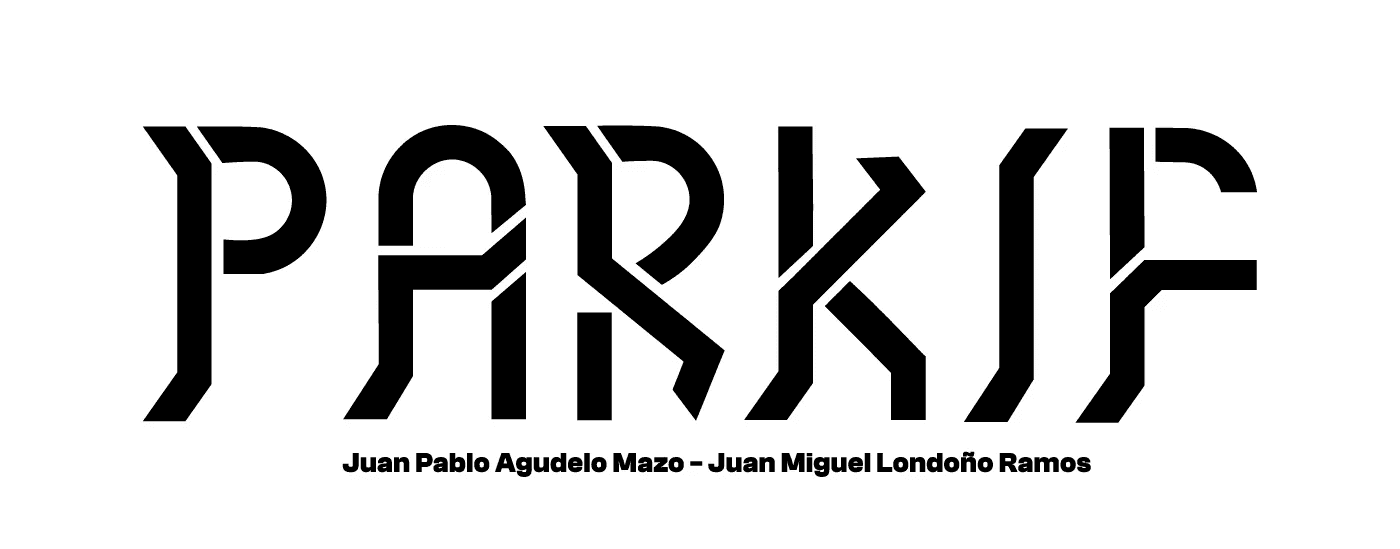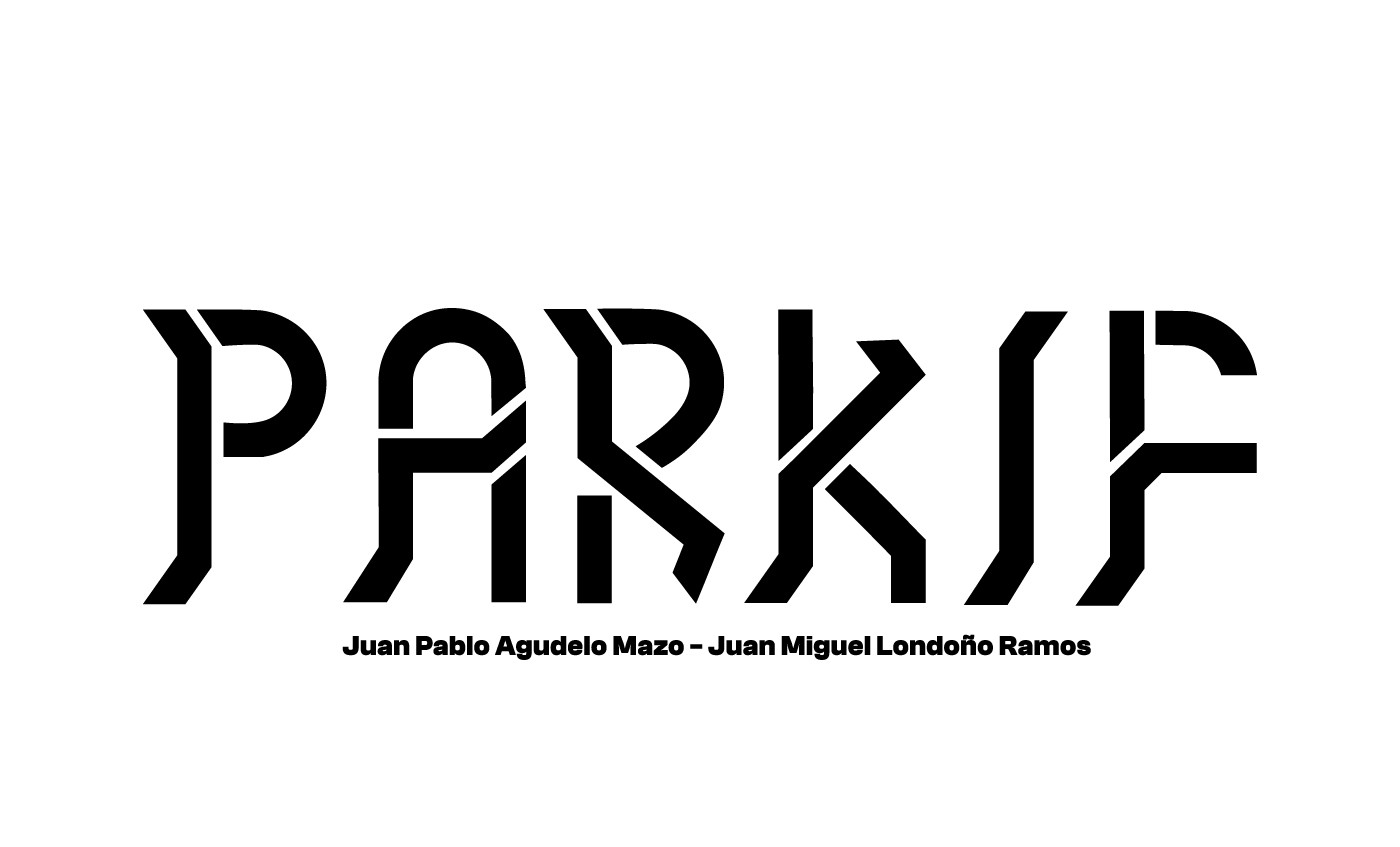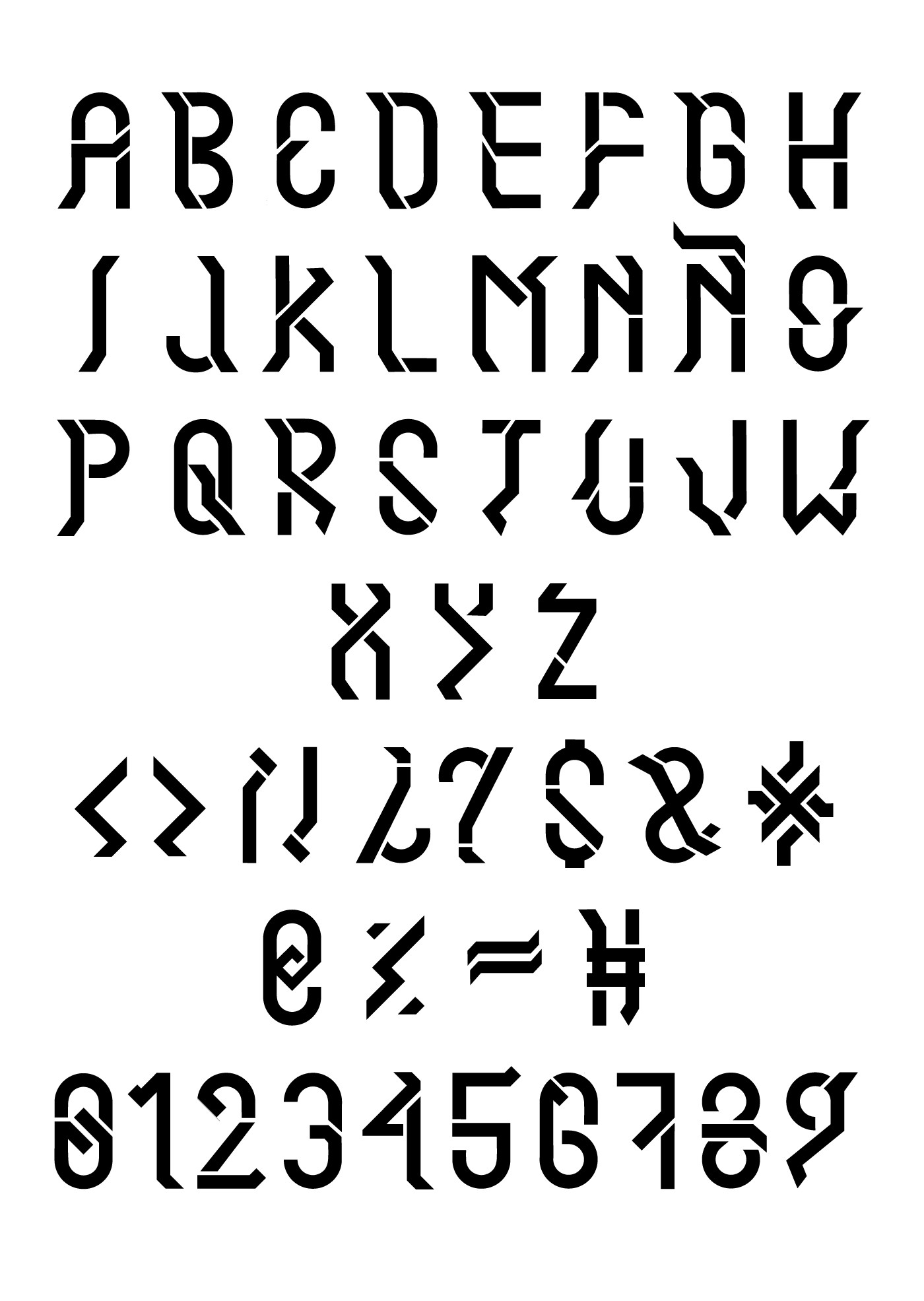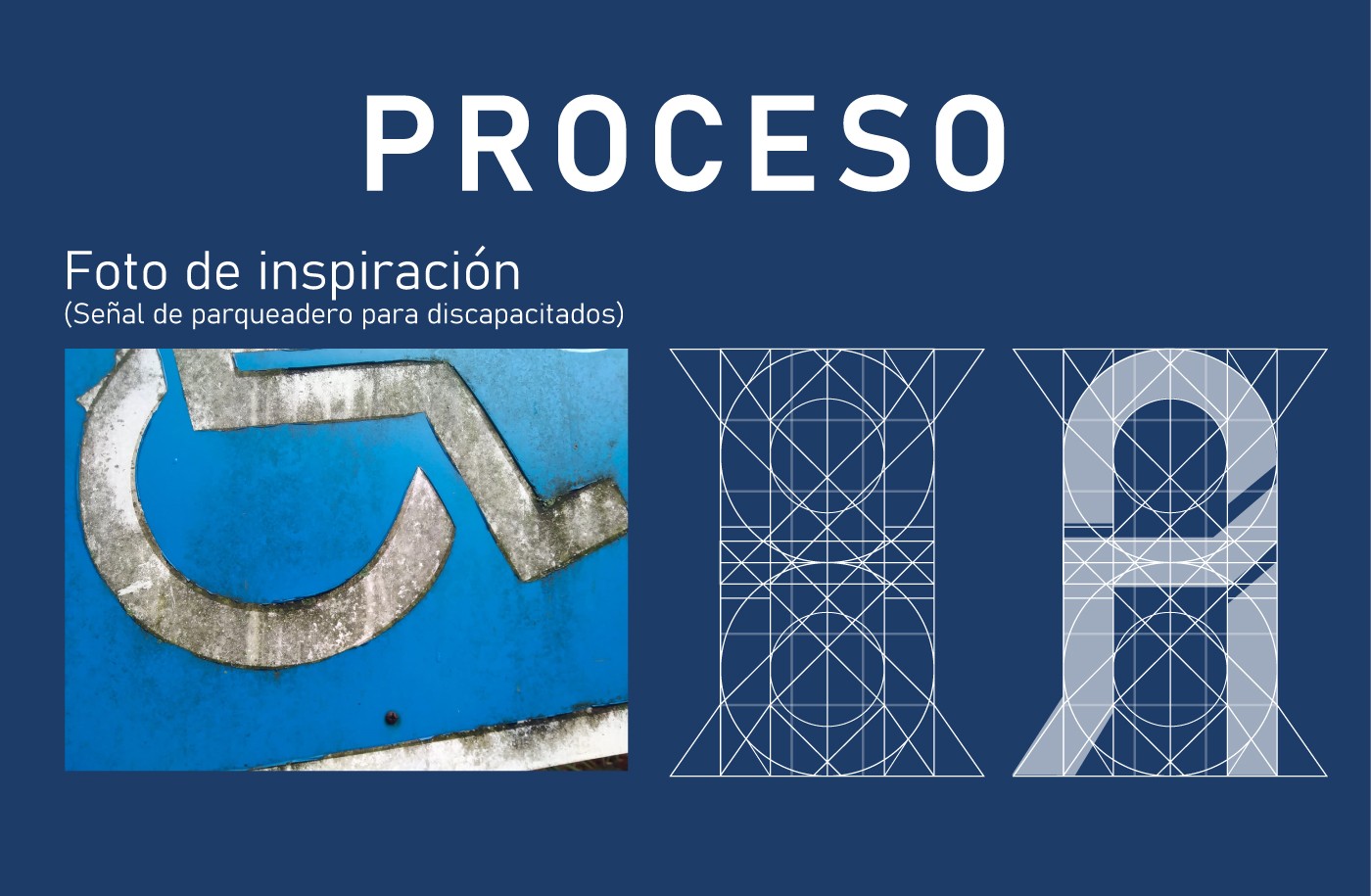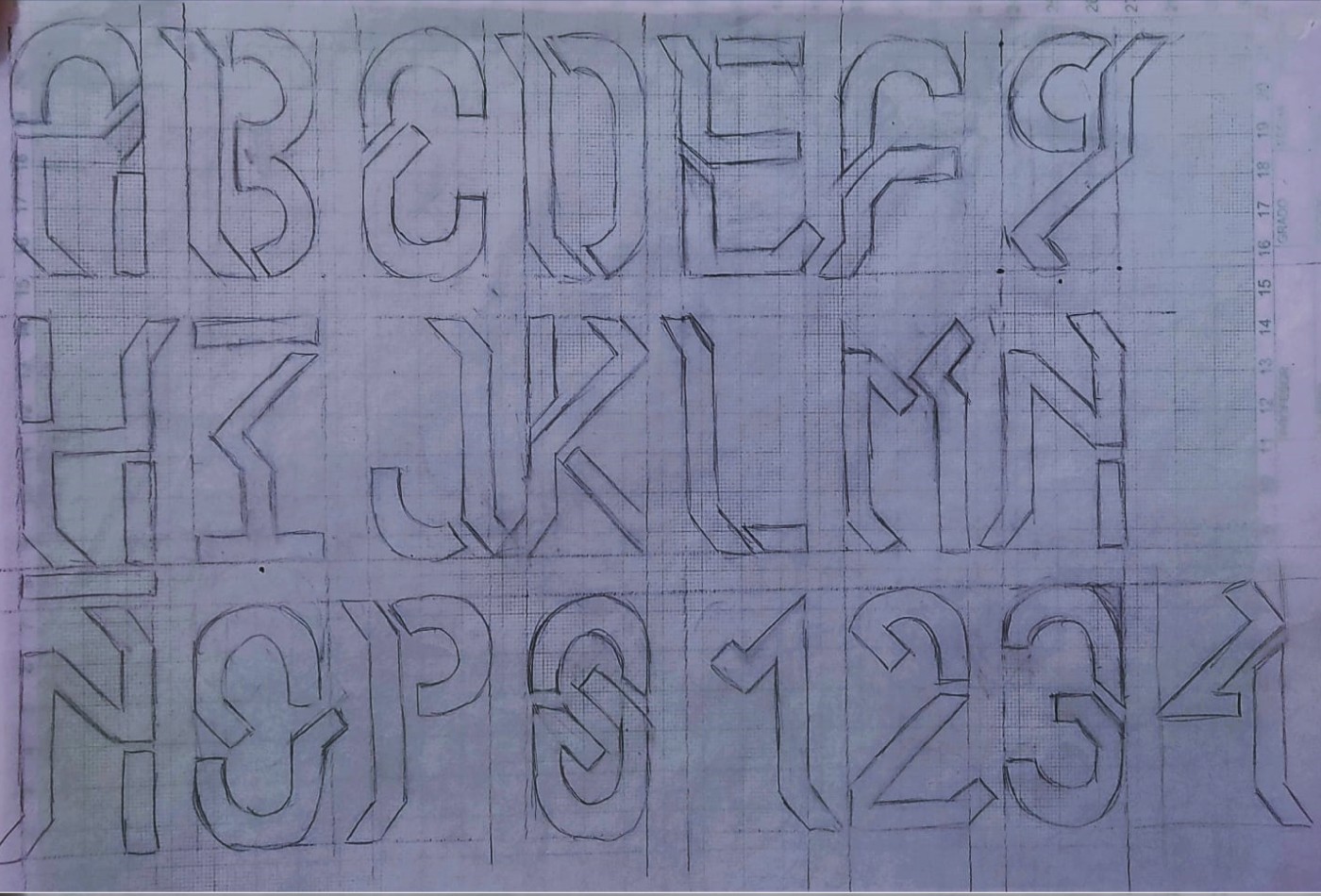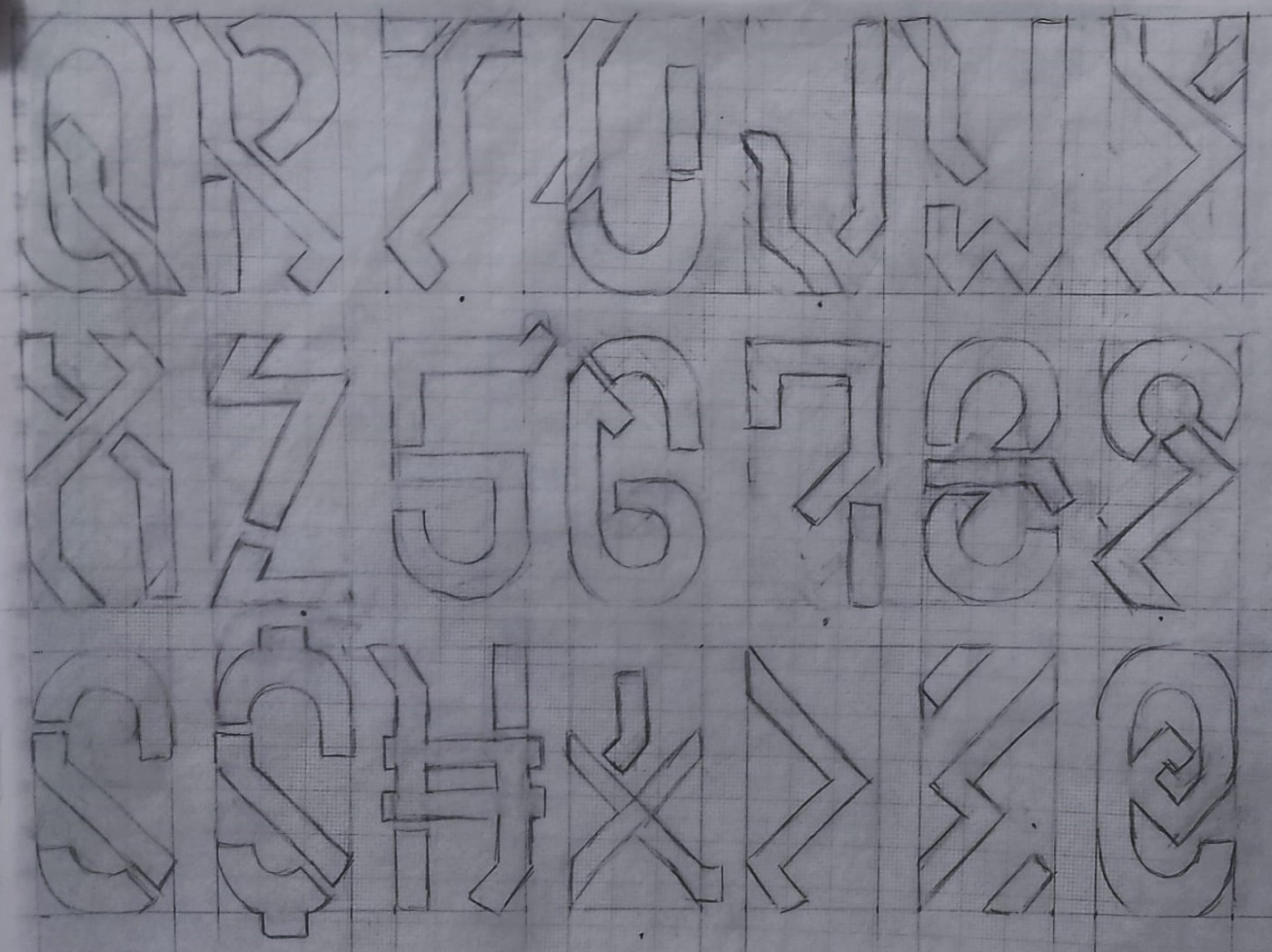
Descripción
Desde una imagen iconográfica que se encuentra en un entorno cotidiano se realizó un alfabeto completo con un estilo disruptivo, tecnológico y moderno.